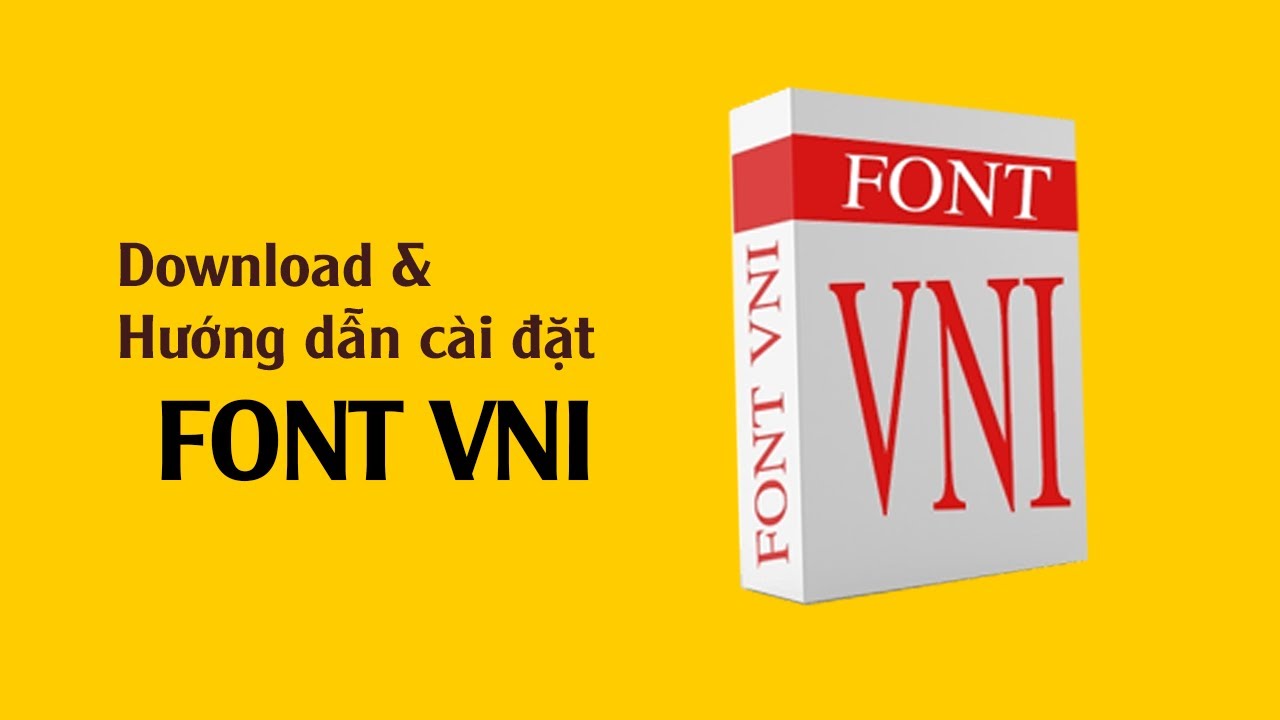
Giới thiệu về Font VNI
Trong thời đại công nghệ thông tin hiện nay, việc lựa chọn một font chữ phù hợp để sử dụng trong văn bản là rất quan trọng, đặc biệt là với ngôn ngữ tiếng Việt. Font VNI không chỉ đơn thuần là một bộ font chữ mà còn mang ý nghĩa văn hóa sâu sắc, phản ánh sự phát triển của ngôn ngữ và công nghệ trong bối cảnh toàn cầu hóa.
Lịch sử và nguồn gốc của Font VNI
Font VNI được ra đời vào cuối thế kỷ 20, trong thời kỳ mà Internet bắt đầu phát triển mạnh mẽ. Với sự xuất hiện của máy tính và nhu cầu sử dụng tiếng Việt trên nền tảng số ngày càng cao, các nhà phát triển đã nhận thấy cần thiết phải tạo ra một bộ font chữ tương thích với tiếng Việt. Điều này đã dẫn đến việc hình thành Font VNI, nhằm mục đích hỗ trợ người dùng trong việc gõ chữ tiếng Việt một cách dễ dàng hơn.
Sự phát triển của font VNI gắn liền với các phần mềm văn phòng và trình soạn thảo văn bản. Font VNI đã nhanh chóng trở thành một trong những lựa chọn hàng đầu cho người dùng Việt Nam. Khả năng hiển thị rõ nét và dễ đọc đã khiến nó trở thành một phần không thể thiếu trong nhiều tài liệu, bài báo và sản phẩm đồ họa.
Vai trò của Font VNI trong việc sử dụng tiếng Việt
Bên cạnh việc cung cấp khả năng gõ chữ, Font VNI còn đóng vai trò quan trọng trong việc bảo tồn và phát triển ngôn ngữ tiếng Việt. Sử dụng Font VNI trong các tài liệu, sách báo hay trang web là một cách để khẳng định bản sắc văn hóa dân tộc. Bằng cách sử dụng font chữ này, người dùng không chỉ thể hiện sự tinh tế trong văn bản mà còn góp phần nâng cao nhận thức về ngôn ngữ và văn hóa Việt Nam.
Hơn nữa, Font VNI cũng hỗ trợ rất tốt cho các nhà thiết kế đồ họa, giúp họ tạo ra những sản phẩm truyền thông ấn tượng và chuyên nghiệp. Qua đó, Font VNI góp phần thúc đẩy sự phát triển của ngành công nghiệp thiết kế tại Việt Nam.
So sánh Font VNI với các loại font khác
Khi so sánh Font VNI với các loại font khác, ta có thể thấy rằng mỗi loại font đều có điểm mạnh và điểm yếu riêng. Font VNI nổi bật với khả năng hiển thị tốt trên nhiều nền tảng khác nhau, từ máy tính đến điện thoại di động. Nó cũng rất dễ dàng để cài đặt và sử dụng, điều này đã làm cho nó trở thành một lựa chọn phổ biến cho nhiều người dùng.
Ngược lại, một số font khác như Arial hay Times New Roman thường gặp khó khăn khi hiển thị các ký tự đặc trưng của tiếng Việt. Điều này có thể gây ra sự không đồng nhất trong văn bản, làm giảm chất lượng nội dung. Vì vậy, đối với những ai thường xuyên làm việc với tiếng Việt, việc lựa chọn Font VNI là một quyết định thông minh và cần thiết.
Các loại Font VNI phổ biến
Trong thế giới đa dạng của font chữ, Font VNI bao gồm nhiều loại khác nhau, mỗi loại mang một phong cách và ứng dụng riêng. Bằng cách hiểu rõ về các loại font này, bạn có thể tối ưu hóa trải nghiệm sử dụng của mình.
Các dòng font VNI thông dụng
Có rất nhiều dòng font VNI khác nhau, nhưng một số cái tên nổi bật nhất bao gồm VNI-Times, VNI-Arial, VNI-Helve, và VNI-Viet. Mỗi loại font này đều có những đặc điểm riêng biệt, phù hợp với từng nhu cầu sử dụng cụ thể.
VNI-Times là một trong những dòng font được ưa chuộng nhất trong môi trường văn phòng. Với kiểu dáng cổ điển và dễ đọc, nó thường được sử dụng trong các tài liệu chính thức hoặc học thuật. Trong khi đó, VNI-Arial lại mang đến cảm giác hiện đại và trẻ trung, thích hợp cho các thiết kế đồ họa sáng tạo.
Đặc điểm và ứng dụng của từng loại font VNI
Mỗi loại Font VNI đều có những đặc điểm nổi bật. VNI-Times, với đường nét thanh thoát, thích hợp cho các bài viết dài và tài liệu cần sự trang trọng. VNI-Arial, với thiết kế đơn giản nhưng hiện đại, thường được sử dụng trong các trang web và tài liệu quảng cáo.
VNI-Helve lại mang phong cách sans-serif, giúp tạo cảm giác thân thiện và dễ tiếp cận. Thường được sử dụng cho các sản phẩm truyền thông xã hội và các trang web thương mại điện tử. Cuối cùng, VNI-Viet thì phù hợp cho các thiết kế mang tính văn hóa, thể hiện rõ nét bản sắc dân tộc.
Hướng dẫn chọn font VNI phù hợp với nhu cầu sử dụng
Việc lựa chọn font chữ phù hợp không chỉ dựa vào sở thích cá nhân mà còn cần phải cân nhắc đến nội dung và mục đích sử dụng. Nếu bạn đang làm việc với các tài liệu học thuật, hãy ưu tiên chọn VNI-Times. Ngược lại, nếu bạn muốn thiết kế một poster hấp dẫn, VNI-Arial hoặc VNI-Helve có thể là lựa chọn tốt hơn.
Ngoài ra, cũng cần xem xét đến đối tượng người đọc. Nếu đối tượng là những người lớn tuổi, nên chọn các font có độ rõ nét cao để dễ đọc hơn. Còn nếu đối tượng là giới trẻ, bạn có thể tự do sáng tạo với các font hiện đại như VNI-Viet.